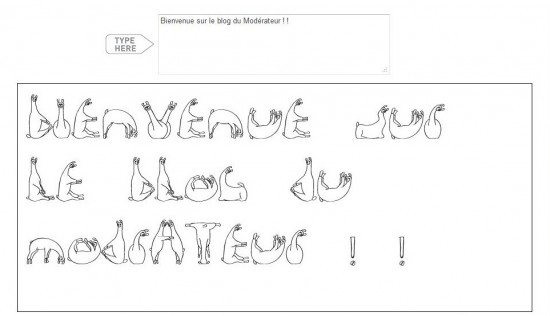
Des lamas, du fromage et des polices : what the font ?
Besoin d’un peu de détente par une dure journée de travail ? Malheureusement, Facebook est bloqué et c’est délicat de sortir votre bouquin du sac ! J’ai ce qu’il vous faut dans le genre inutile mais divertissant. On vous a déjà appris à parler kikoolol avec Lolify ou encore indiqué les sites sur lesquels jouer en ligne pour faire une bonne pause ! Cette fois-ci vous allez écrire en llamafont. Et oui cette écriture existe et c’est plutôt sympa. Le nom ne trompe pas c’est bien des lamas qui forment les lettres. Cela marche exactement comme Google translate. Il vous suffit d’écrire votre texte et il est traduit en llamafont. Voyez plus tôt :
Vous n’y passerez surement pas des heures mais je suis sur que vous vous prendrez au jeu. Autre moyen de se détendre entre deux gros dossiers avec Cheeseorfont. Ceci est un jeu. Le principe est très simple. Un nom vous est proposé, vous devez deviner si c’est un nom de fromage ou un nom de police d’écriture. Je pense que vous serez surpris de voir que ce n’est pas si facile que ça ! A vous de tester.
Et un petit dernier pour la route et pour être raccord avec le titre, What the font vous permet de retrouver une police d’écriture à partir d’une copie écran. Cela peut être pratique.